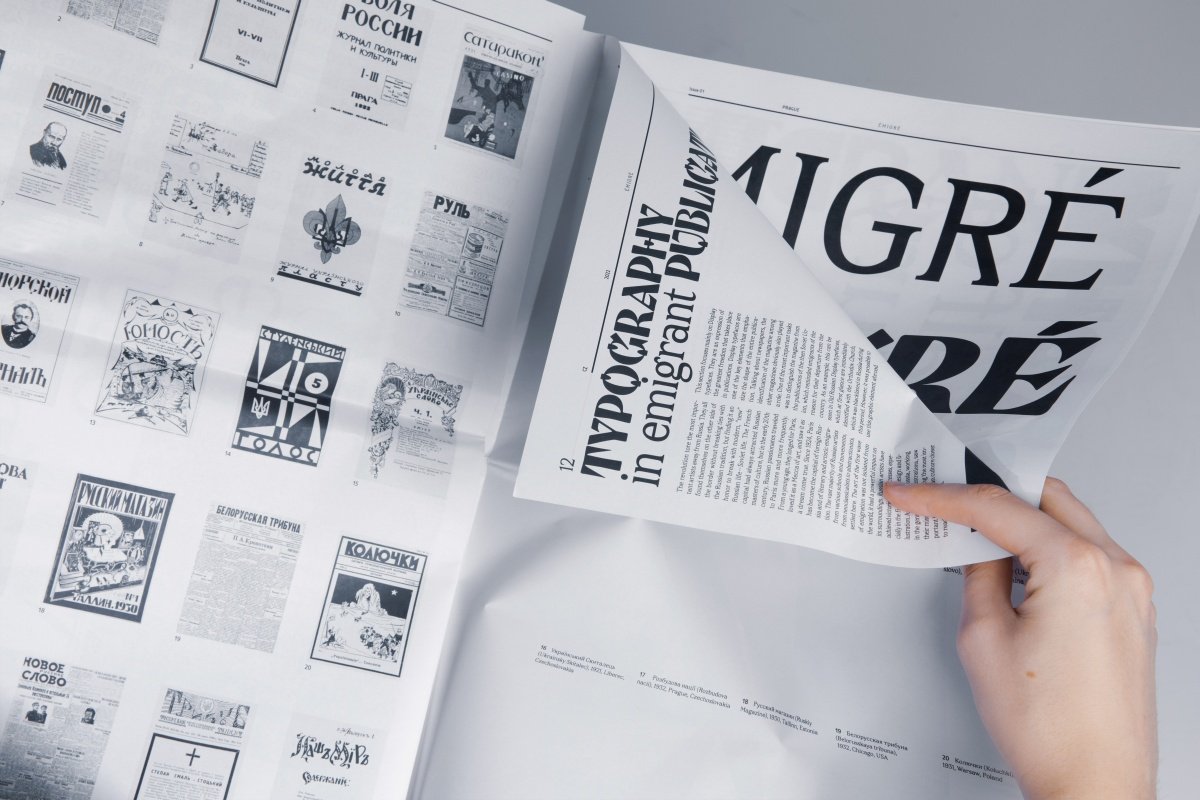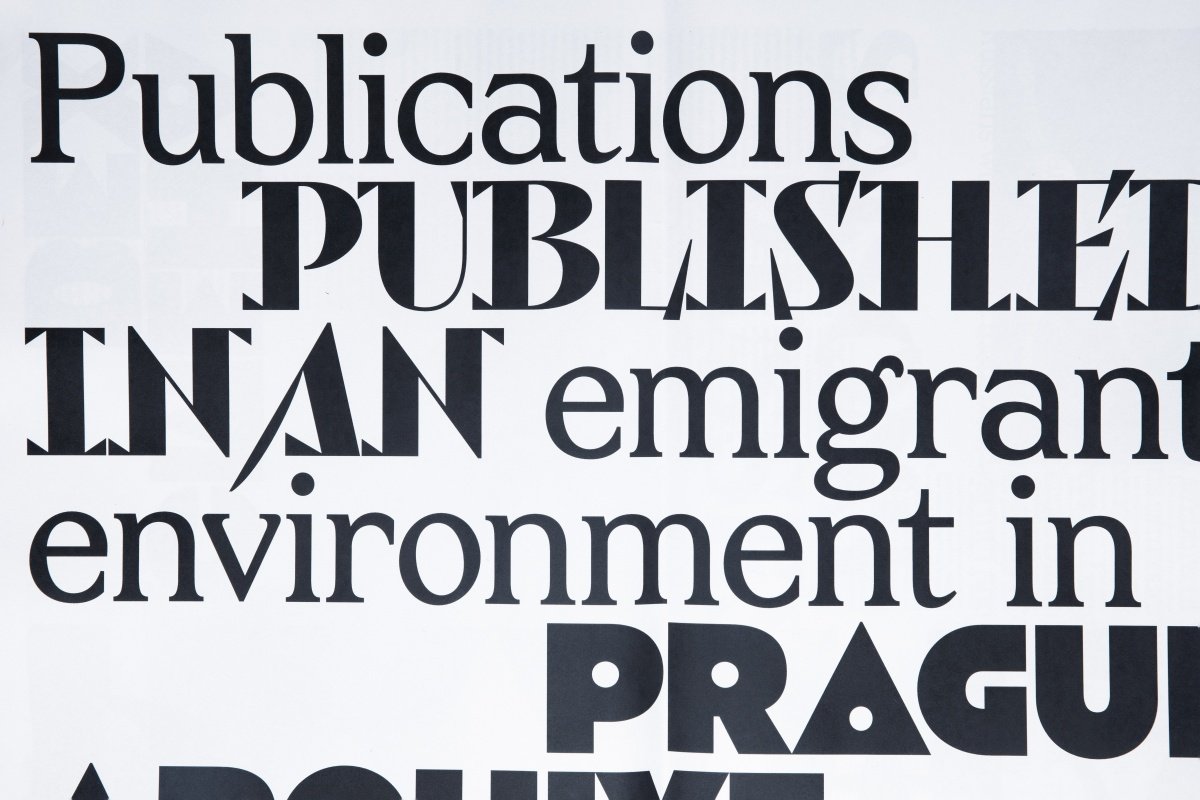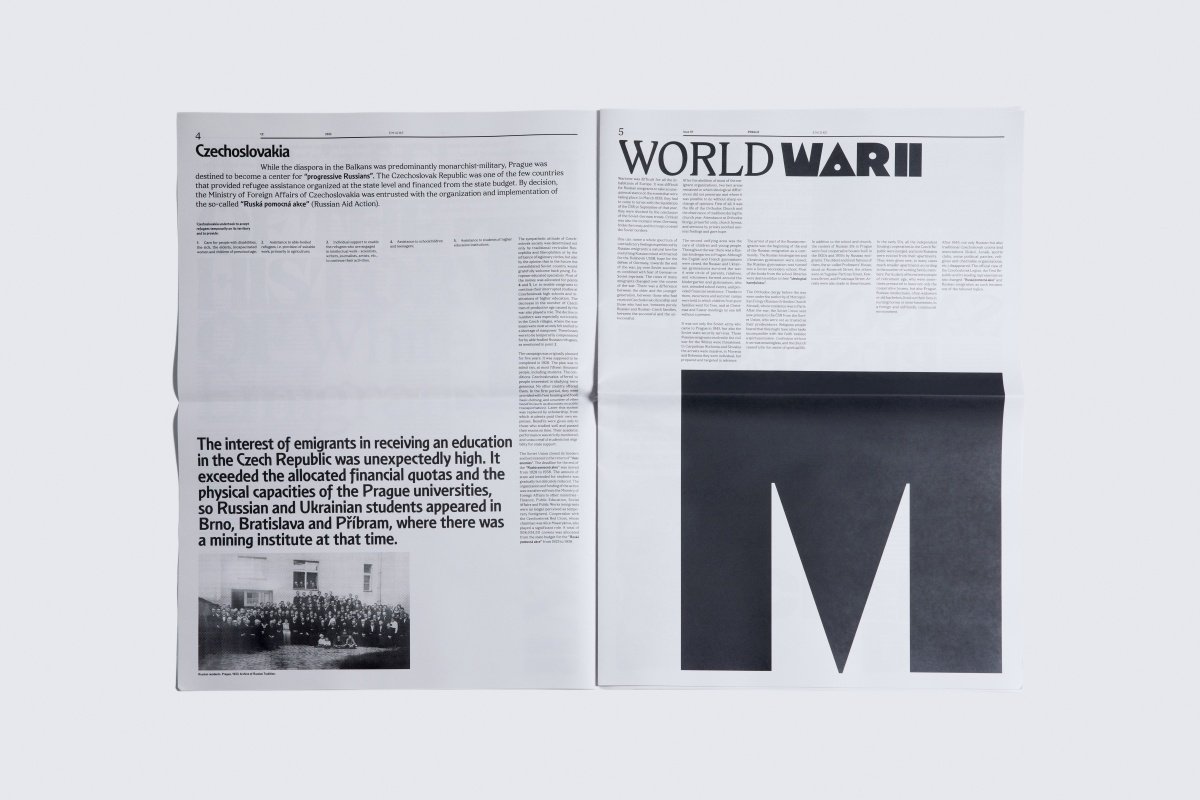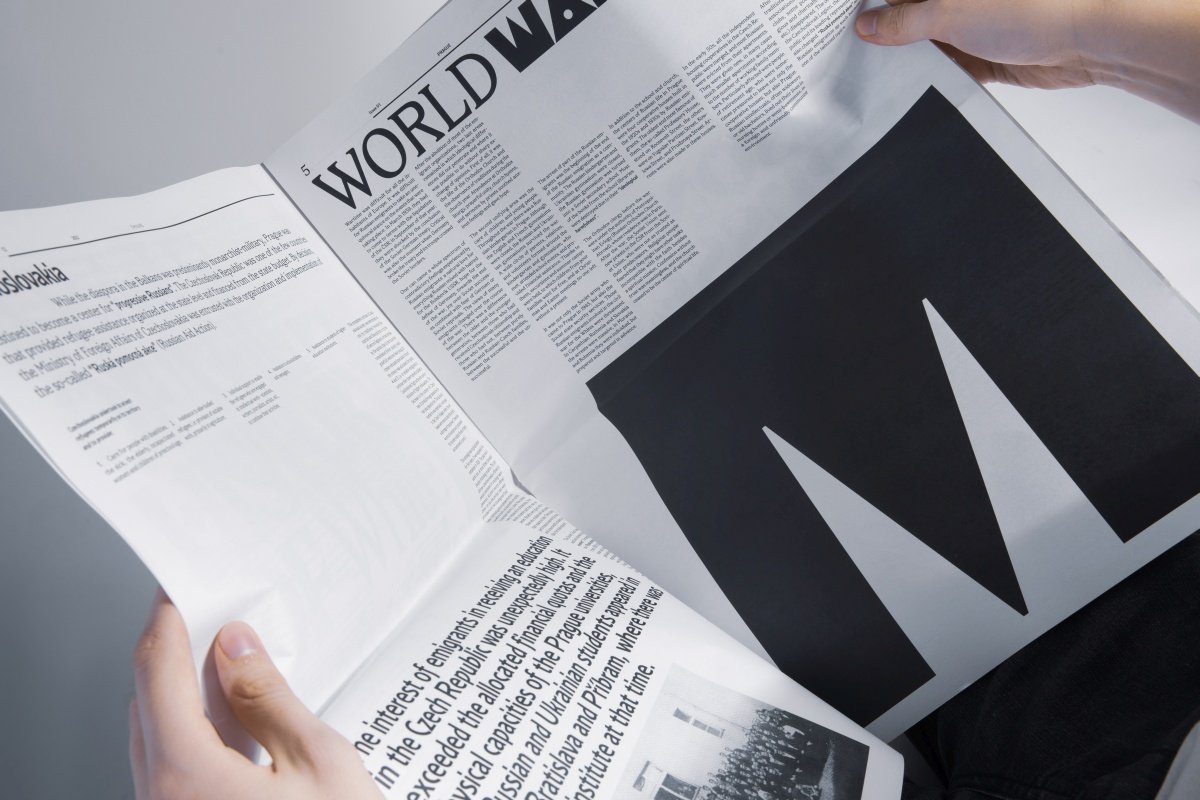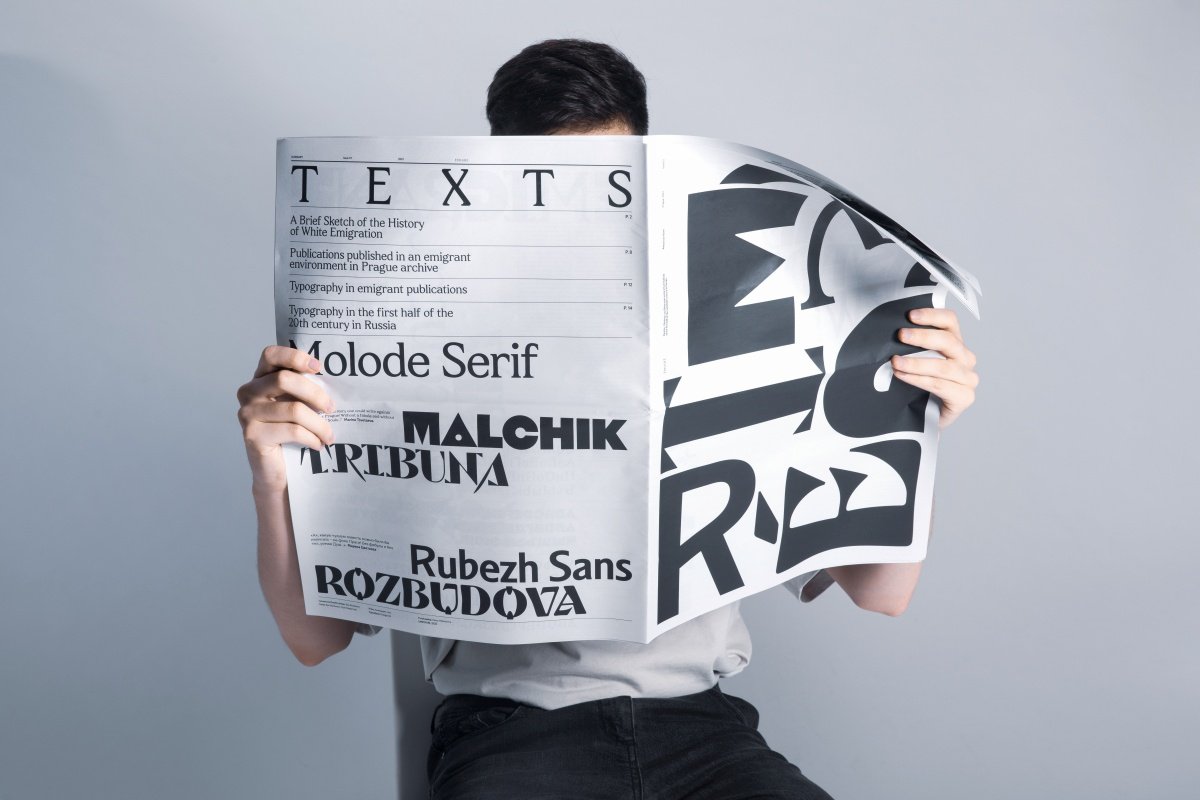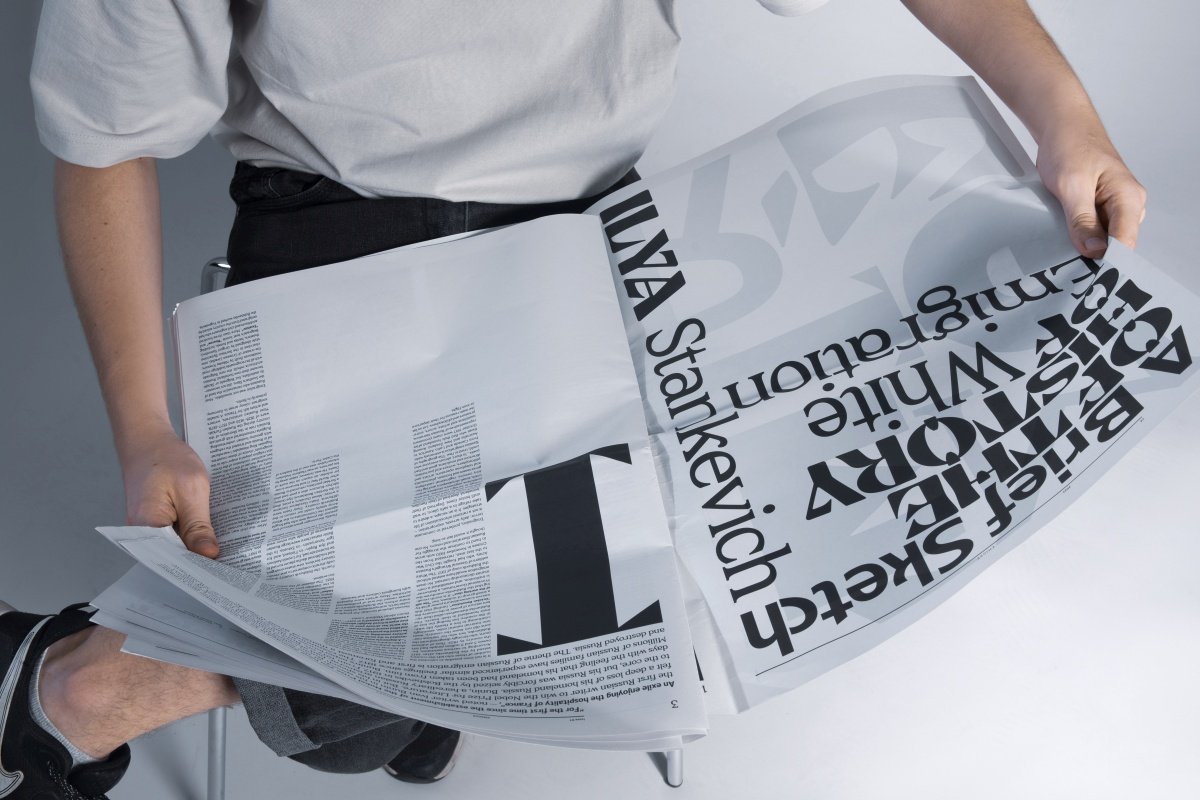
Čerstvý absolvent Ateliéru tvorby písma a typografie UMPRUM Ilya Bazhanov získal ocenění v mezinárodní soutěži vyhlašované Type Directors Club. Certifikát TDC69 za vynikající typografické zpracování obdržel v kategorii Typografie za svou diplomovou práci ÉMIGRÉ.
ÉMIGRÉ Ilyi Bazahanova se snaží formou obsáhlé historické studie emigrantských publikací první půlky dvacátého století v zahraničí o analýzu a porozumění schématům, kterými se emigranti snažili zachovávat vlastní identitu a svébytnost. Výsledkem zkoumání je interpretace pojetí zachování vlastní kultury v cizím prostředí, apropriace vnějšího světa do vlastní tvorby a naopak. V návaznosti na tento výzkum vznikla publikace formou novin a písmová rodina na základě historických předloh ze Slovanské knihovny v Praze.